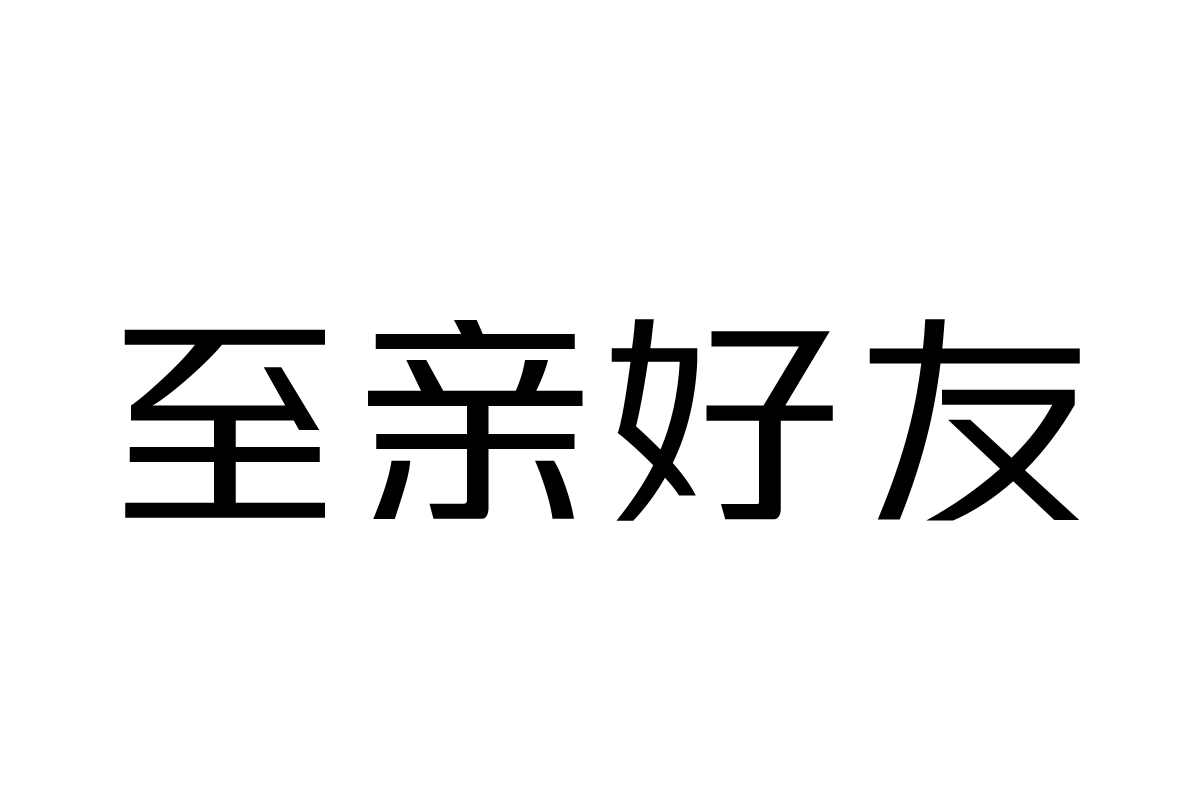
三极力量酷黑细字体是一款专为需要强调视觉效果的场合设计的字体。它以其独特的设计元素和风格,为文字赋予了强烈的视觉冲击力和吸引力。这款字体的特点在于其精细的笔画和结构,使得文字在阅读时更加清晰易读。同时,它的线条流畅而有力,给人一种强烈的视觉冲击感。无论是用于广告、海报、书籍封面还是网页设计,都能展现出其独特的魅力。